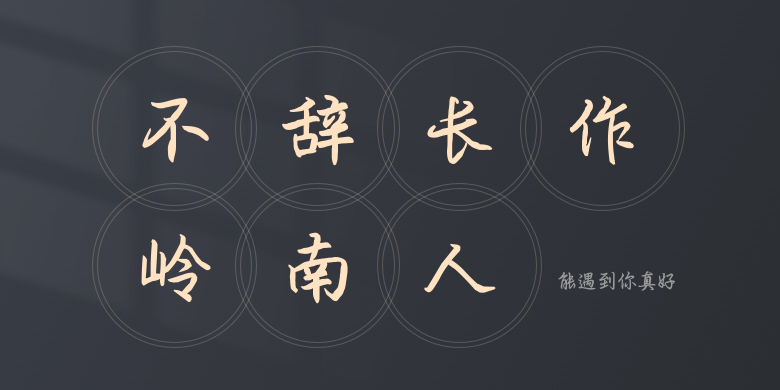
能遇到你真好
能遇到你真好,这款字体结构工整、笔画清晰,兼顾美观与易读性,适用于标题、正文、海报、包装、LOGO 等多种场景。字形优雅稳定,风格百搭耐看,适配日常排版与创意设计,让文字呈现更舒适、更具质感。能遇到你真好一笔一画,皆是细节,以均衡的比例、流畅的线条打造舒适视觉体验,字形端正大气,风格简约现代。无论是商业设计、品牌宣传还是日常排版,都能轻松驾驭,让文字更有格调与力量。能遇到你真好字体下载。